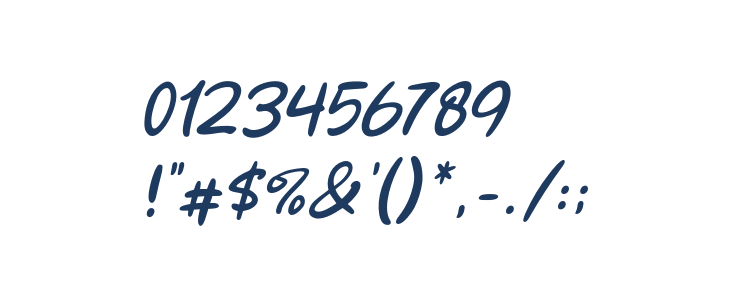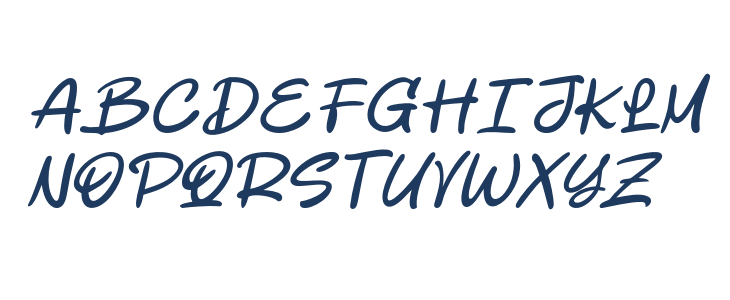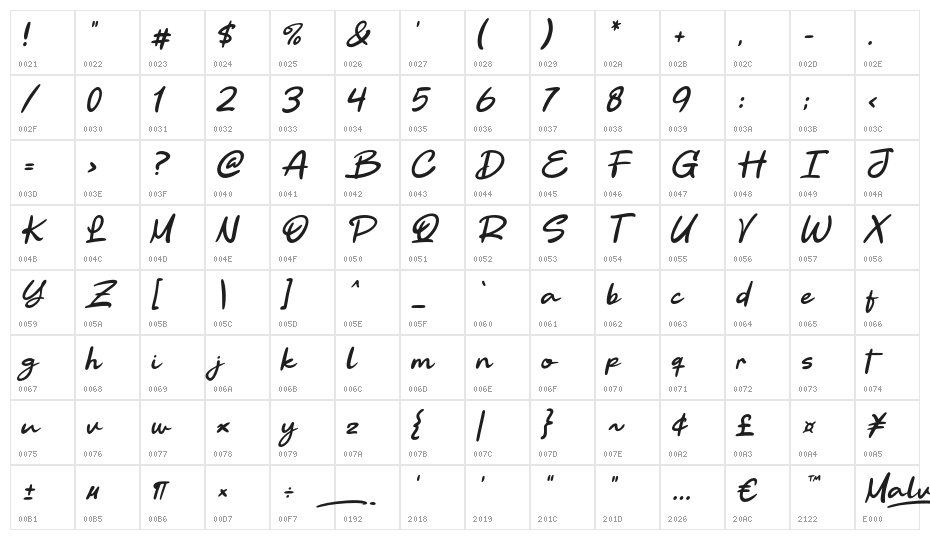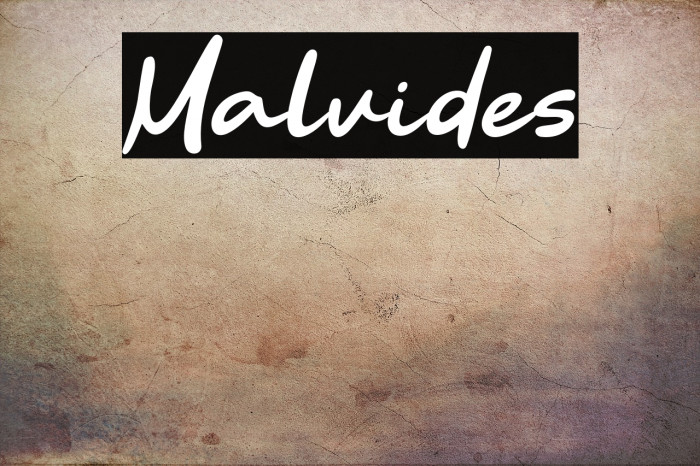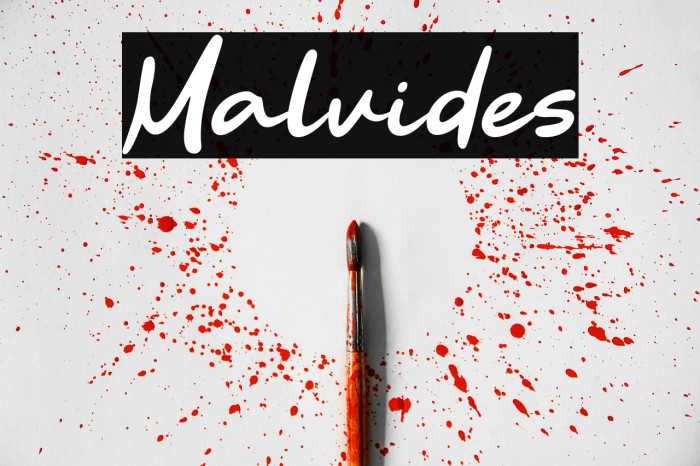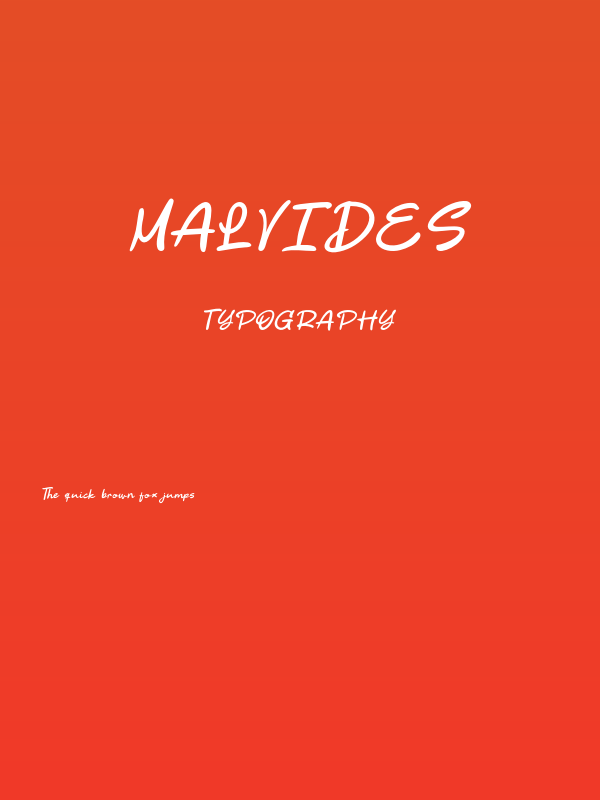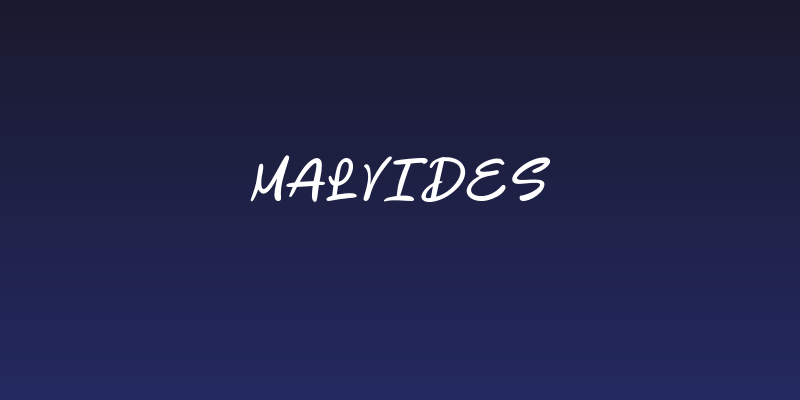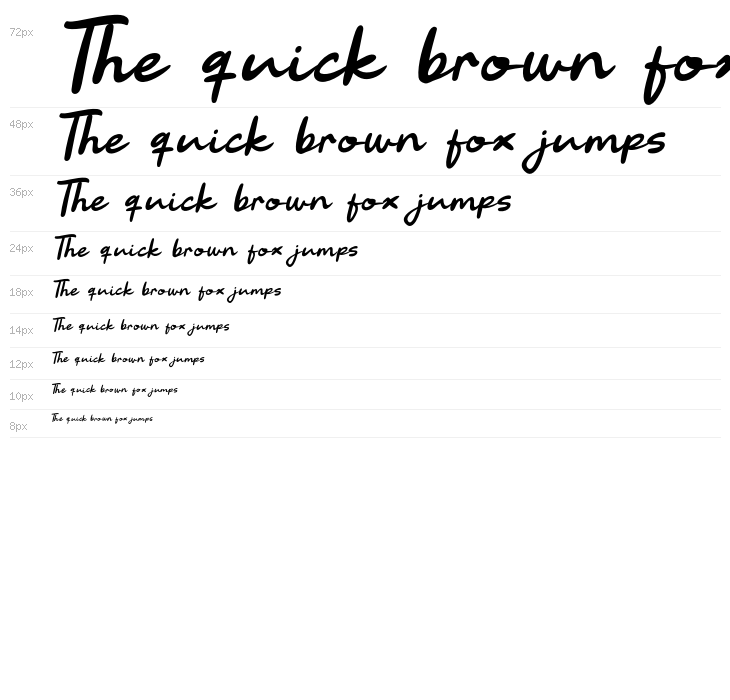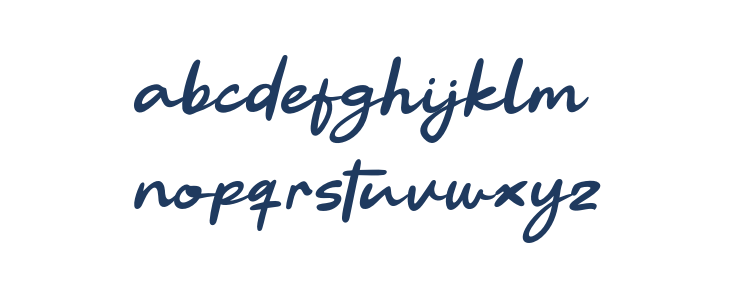
Malvides Font
| Gesamtstil | Casual, friendly, and approachable |
| Anwendungsfall | Logos, headlines, invitations, and informal text |
| Vorgeschlagene Projekte | Invitations, greeting cards, branding, social media graphics, and informal documents. |